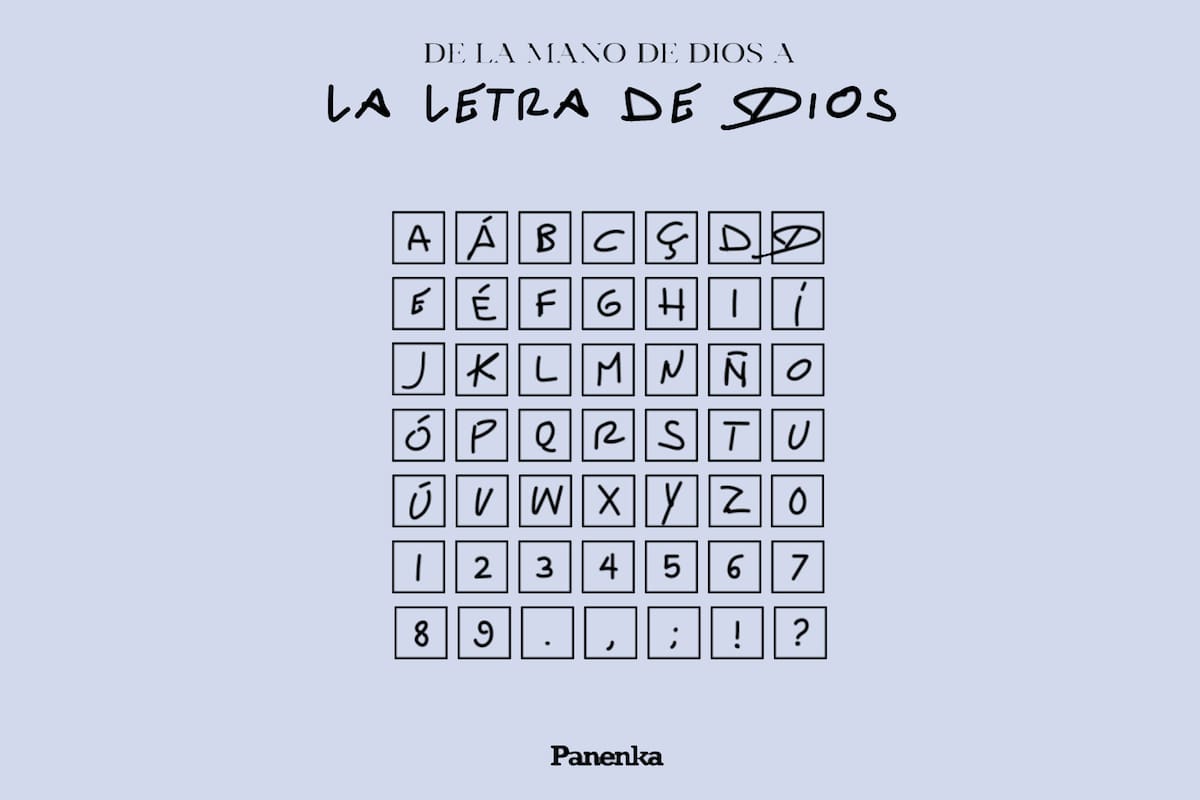
La revista española Panenka vuelve a sorprender. Su edición de noviembre está dedicada a Diego Armando Maradona. Pero con algo llamativo y muy original: la tipografía utilizada fue creada especialmente, y está basada en las dedicatorias que el ídolo realizó de puño y letra a lo largo de su vida.
“Nosotros teníamos en mente sacar este mes el número de Maradona para conmemorar el primer aniversario de su muerte, y una agencia de publicidad con la que hemos trabajado anteriormente nos propuso llevar toda la tipografía Maradona a todo el número”, le explica a LA NACION Roger Xuriach, coordinador del primer medio español de cultura futbolística. Y agrega: “Ha sido algo bastante laborioso y artesanal, nos llegó esta idea, nos gustó y lo llevamos adelante con todo el respeto y sensibilidad del mundo, con el agregado de que la tipografía se puede descargar gratuitamente desde nuestra página”.
Según se explica en el sitio, “Diego Armando Maradona escapa a cualquier lógica. Genio y figura tanto dentro como fuera del terreno de juego. Le dejó un legado incalculable al mundo del fútbol. Entre todos esos momentos mágicos destaca uno, ‘La Mano de Dios’. Un símbolo para la eternidad. La mano con la que inspiró a una nación y con la que también escribió miles de dedicatorias en camisetas, postales o balones.”
A partir de esa caligrafía, el staff de Panenka ha deconstruido, con la ayuda de un tipógrafo, todos sus caracteres, creando una fuente original con el carácter del ‘Diez’: ‘La Letra de Dios’.
“La Revista Panenka lanzaba su edición de Noviembre - un número especial e íntegro sobre Maradona - un año después de su muerte y teníamos claro que no podía ser una edición como cualquier otra. Queríamos hacerle un homenaje”, explican desde España Pablo Luna y Marc Xifré, director de Arte y redactor, respectivamente, de la agencia LOLA MullenLowe. Y amplían: “A partir de ahí, nuestro proceso creativo fue el siguiente: Si la Revista Panenka es “El fútbol que se lee”, sería maravilloso que esta edición precisamente estuviera escrita por ‘la mano de Dios’.”
Los ideólogos de este homenaje tan original y sentido, detallan el foco de su trabajo: “Pero, ¿dónde encontrar la letra de Maradona? Pues en un lugar especial: en todas las dedicatorias que le hizo a los fans y aficionados de todo el mundo. Así que, con la ayuda de un tipógrafo profesional, nos pusimos a analizar las camisetas con dedicatorias de El Diego, a extraer letra por letra hasta completar el alfabeto y crear la tipografía “La Letra de Dios”. El resto era digitalizarla y maquetar la revista con la nueva tipografía, algo que Panenka nunca había hecho.
Con relación al impacto que tuvo a nivel mundial, Luna y Xifré comparten: “Ha sido un proceso laborioso pero muy hermoso, sabíamos que estábamos creando algo que a los aficionados del fútbol y de Maradona les iba a llegar al corazón y muy especial para nosotros, futboleros de corazón.
Con esa licencia creativa, el medio español homenajea a Diego en el primer aniversario de su muerte. La Letra de Dios abarca todo el número 112.